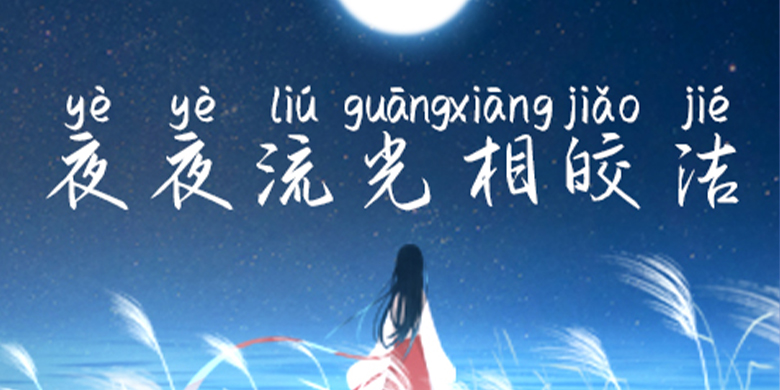
方正手迹-夜夜流光相皎洁
字体品牌: 方正手迹 设计师:罗晓康 字体分类:创意书写 字体属性:精品字 字符集:简繁扩展(GBK) 发布时间: 2020
夜夜流光相皎洁是一款随性自然的手写体。该字体结构比较随性,跳出方方正正的感觉,笔画的连贯流畅展示出随性自然。该字体适用于文艺类的书刊、品牌广告和产品包装设计,以及社交网络的个性化用字。